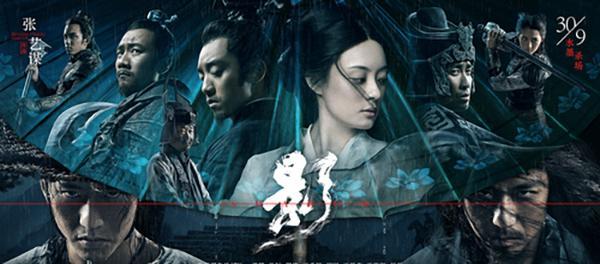
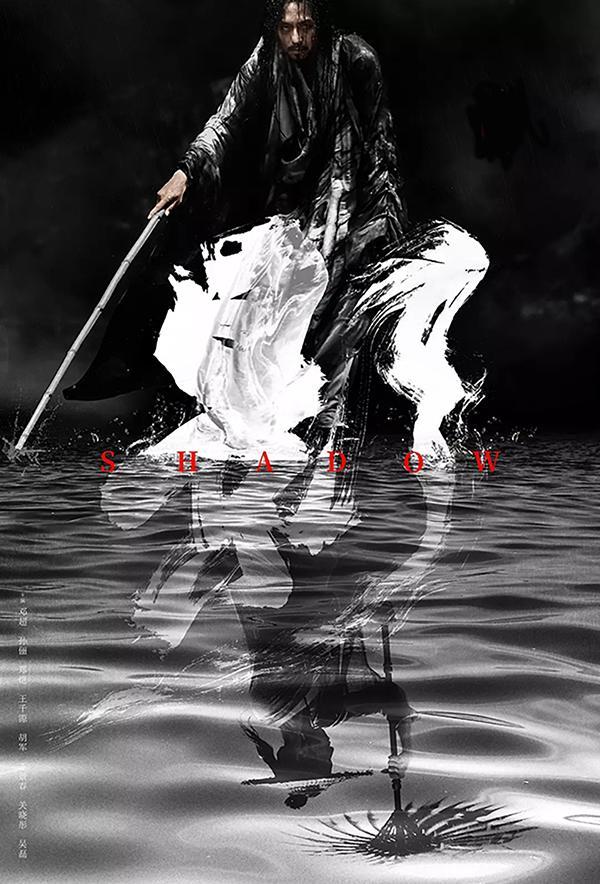
整个电影给我们带来的感觉是浓厚的水墨中国风种,且从演员的服装到配饰的雕琢,从背景的布置到细节的处理都是统一的水墨色彩。有人可能会有疑问?这样的单一水墨风格会不会太单调。其它的电影或者是电视可能会有出现这种情况,但是这个电影却丝毫不会,相反正是因为这个“单一”的水墨风格更加让人被吸引,更是带给别人不一样的好体验。
那么张艺谋的电影《影》为何会使用这个海报字体呢?
个人认为一个好的海报字体设计并不仅仅只是说在这个字上设计的有多好,能够多吸引人,而是能否更多的去想表达想要去表达的内容。例如:你开了一个甜品店然后店名的字体设计却表达的是火锅的设计概念,这样子的话无论你这个字体设计的多好看,多吸引着人,但是你这个字体设计却没有表达出你想要表达出的东西,那这样子也是毫无意义的。同样的,在我看来电影海报字体设计同样也是一样的,字体设计师更多的是去设计出与该内容相关的字,就像在一部战争片,里面充满的是战斗和激情,设计的海报字体应该是类似于硬黑这类的风格,但是如果设计方向是往温柔可爱的方向的,那么就与该内容相违和了,即使你设计的再好看也是无意义的,因为一个设计,更多的是要去设计出想要表达的内容,而不仅仅只是局限在好看程度。
而电影《影》的海报字体设计则是完全的表达出了该电影的内容,因为刚才已经说过,整个电影的风格给我们带来的感觉是浓厚的水墨中国风种,所以电影字体设计用毛笔设计的写法在适合不过。且该字写法近似于行草这类,选用这种风格设计,个人觉得也是非常的合理。因为该电影只有一个字“影”,如果说用正楷,或者是黑体这类风格去写,个人认为未免觉得过于单调。此外个人认为既然是用中国古代的书法去写,那么写"潦草"的书法个人是觉得更加的具有代表性和观赏性的。
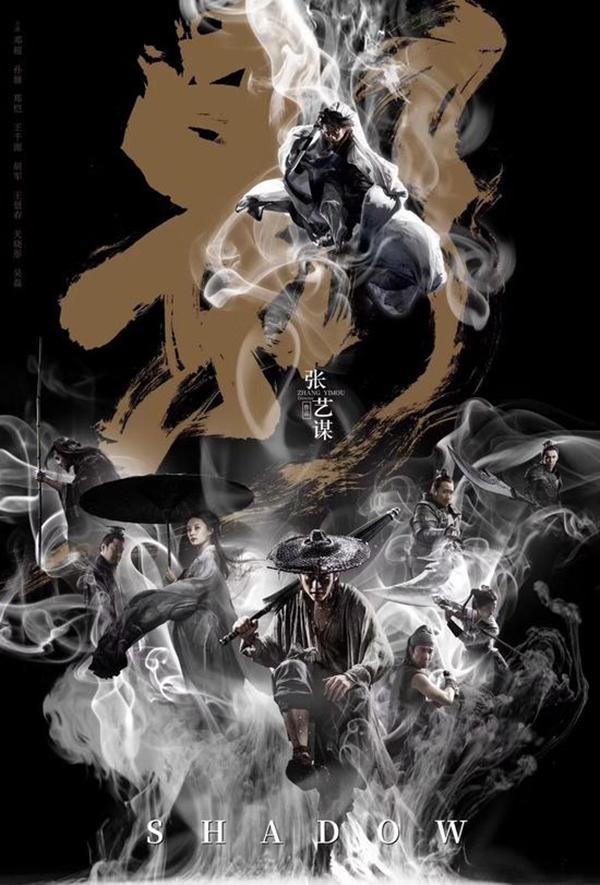
此外,该电影海报字体的设计除了符合该电影风格,单单从这个字上面讲写的也是十分的不错,所以个人觉得写这个“影”字的书法设计师是非常的棒的!也是让本人不得不佩服的。另外对该电影海报字体有什么其他看法和想说的也可以在下面积极评论。